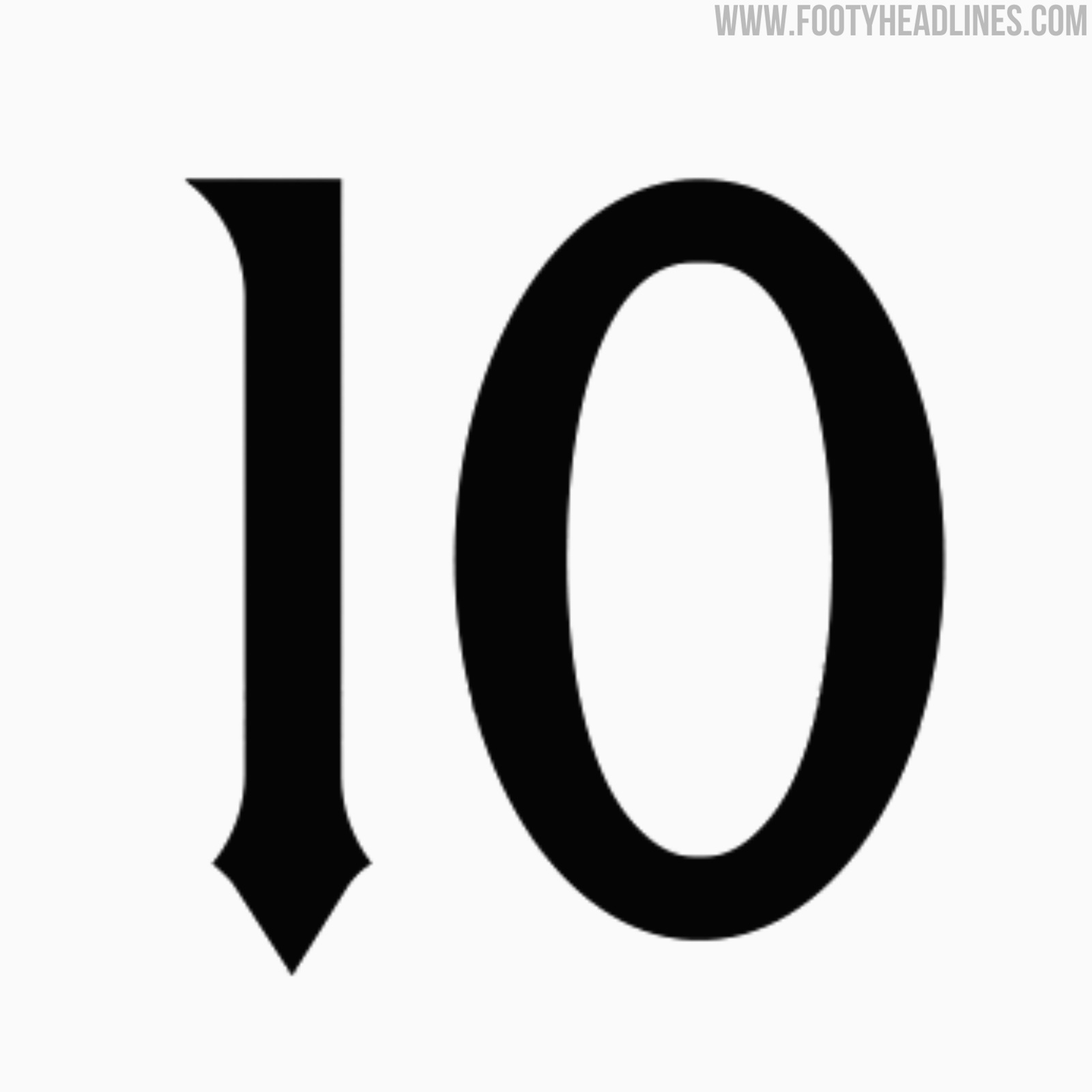
Die Schriftart für das Trikot von Manchester United 25-26 „Trident” wurde veröffentlicht
- Neue Trikot-Schriftart: Manchester United hat anscheinend die neue Schriftart für die Trikots der Saison 2025-2026 in einem Teaser-Video gezeigt.
- Design der Schriftart: Die mögliche Trikot-Schriftart für die Saison 2025/26 hat einen klassischen Serifenstil mit klaren Zahlen und auffälligen Details.
- Offizielle Vorstellung: Die neue Schriftart wird am 12. Juni 2025 zusammen mit dem Heimtrikot von Manchester United für die Saison 2025/26 offiziell vorgestellt.
Update: Die neue Schriftart für die Trikots von Manchester United für die Saison 2015/2016 wurde Mitte Juni vorgestellt und kam während der Sommertour des Vereins in den USA zum ersten Mal zum Einsatz. Sie ist jetzt im offiziellen Fanshop des Vereins erhältlich.
Schriftart des Trikots „Trident” von Manchester United für die Saison 2015/2016
Die Schriftart des neuen Trikots von Manchester United für die Saison 2025/26 hat einen klassischen, eleganten Serifenstil, der vom legendären Dreizacksymbol inspiriert ist.
Die Zahlen sind klar gestaltet und haben coole Details wie die spitze Basis der „1“ und die weichen, traditionellen Kurven der „2“, „5“ und „6“.
Dieses Design sorgt für einen hochwertigen, traditionellen Look, der sich von den moderneren, eckigen Schriftarten vieler anderer Vereine abhebt.
Die Schriftart des neuen Trikots von Man United für 2025–26 basiert immer noch auf der aktuellen Trikot-Schriftart, hat aber ein paar Verbesserungen bei den schrägen Schnitten und abgerundeten Fußenden. Diese Anpassungen verleihen ihr einen klassischeren und raffinierteren Look.
Schriftarten der Trikots von Manchester United 2018–2025
Die neue Schriftart „Manchester United 25026” ist seit Juli 2025 verfügbar.